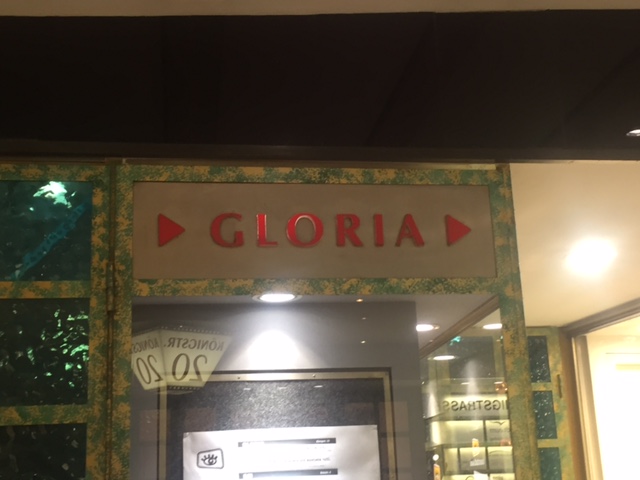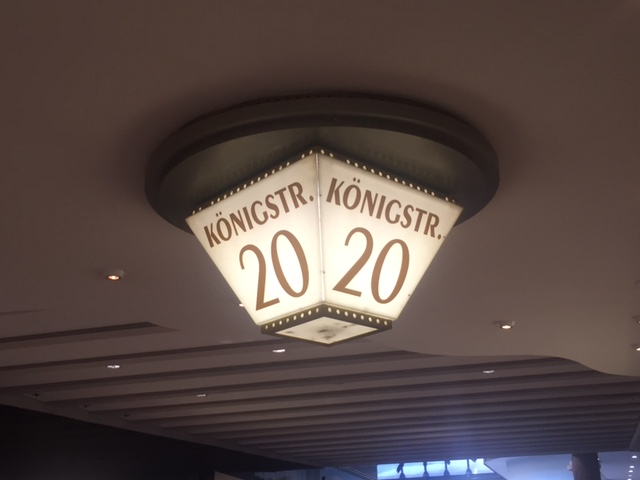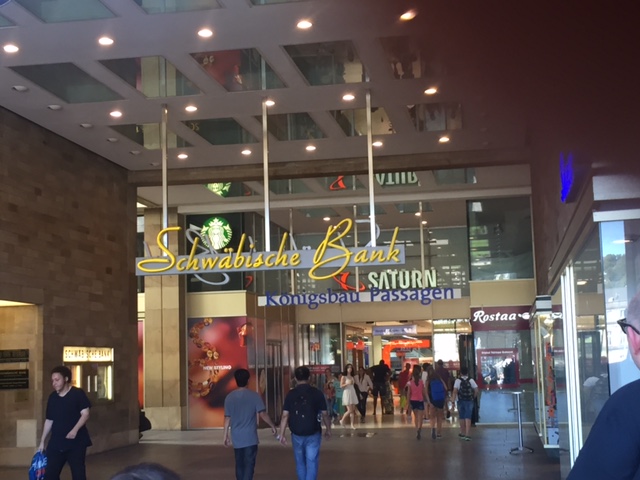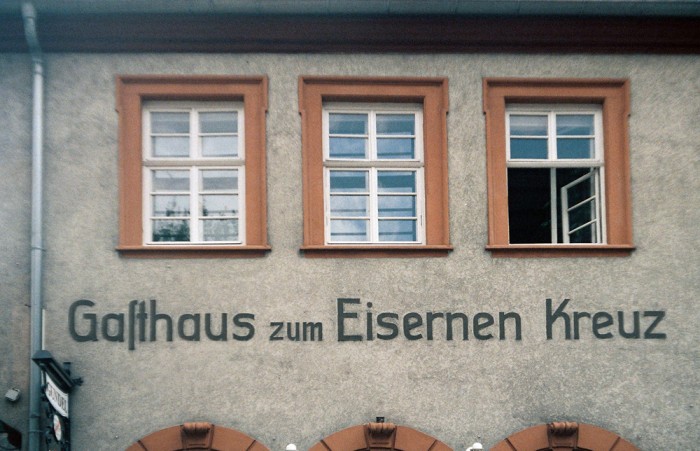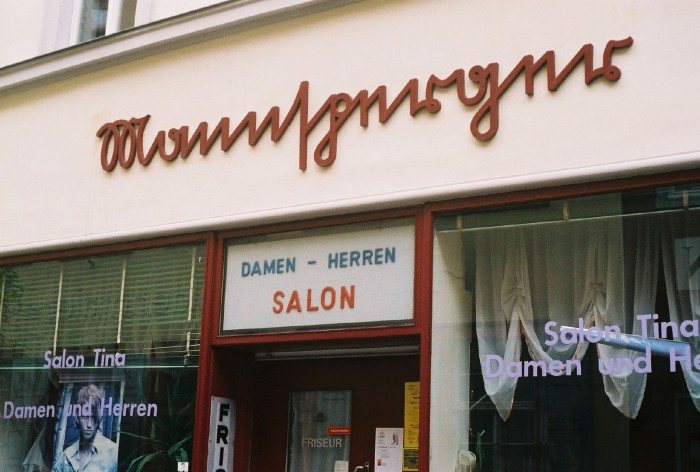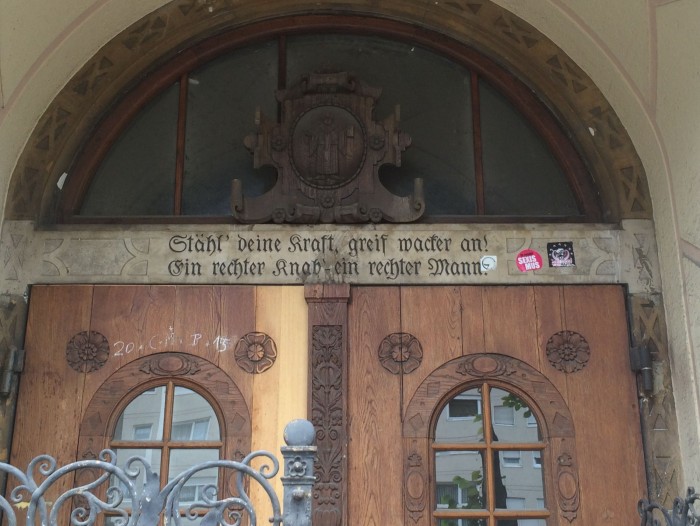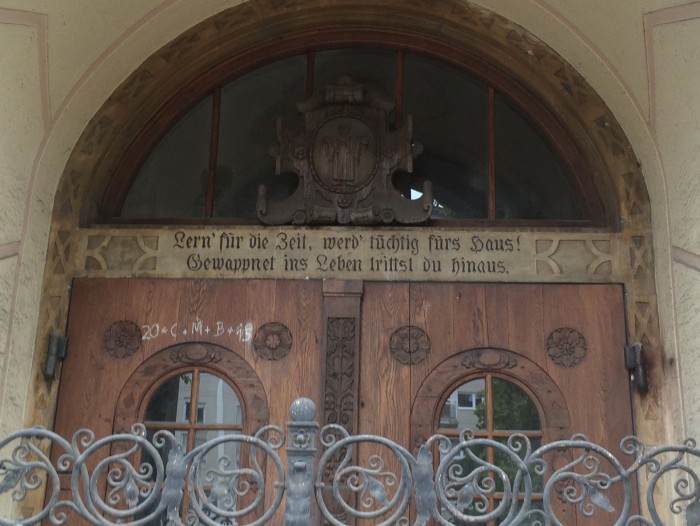
Typostreifzug durch die Stadt ...
Diesen netten Verstoß gegen die Lange-s-Regel habe ich in Heidelberg gesehen. Ist ja auch eine originelle Grotesk.
Und wahrscheinlich wollte der Schreiber ein wenig vom militärischen Ursprung ablenken, und hoffte, dass man an Eis denkt.
... was ihm auf jeden Fall gelungen ist – man sieht in diesen Tagen ziemlich viel Leute mit einem Eis in der Hand dort herumlaufen ;-)
Nochmal Heidelberg: Die meisten von Tinas Kunden werden das wohl eher nicht entziffern können.
Ich nehme an, dass der Schriftzug zu einem alteingesessenen Geschäft gehört hat.
Bei meiner – zugegebenermaßen oberflächlichen – Recherche konnte ich nichts darüber finden.
Sieht wunderschön aus, aber das ſ ist da doch auch falsch, oder? Ich hätte ja gedacht, daß das Manns-perger heißt, nicht Mann-sperger.
aber das ſ ist da doch auch falsch, oder? Ich hätte ja gedacht, daß das Manns-perger heißt, nicht Mann-sperger.
Im Prinzip stimme ich dir zu. Aber solange wir wegen der Herkunft des Namens nicht ganz sicher sein können ...
Die Optik könnte allerdings auch eine Rolle gespielt haben. Vielleicht hätte sich das runde s nicht so gut in den Namenszug eingefügt.
Oder der Name ist eben tatsächlich Mann|sperger. Namen Sperger und mit -sperger, wobei das s eben kein Fugen-s ist kenne ich ein paar.
Das ist dann so Ähnlich wie bei Neckarſulm, das eben auch die falsche Aussprache als das Ulm des Neckars ersat durch Aufgabe des langen s bekommen hart. Heute wissen nwenige, dass die Stadt einfach nur nach den Flüssen benannt wurde, die dort zusammen fließen, eben Neckar + Sulm = NecksrSulm = Neckarſulm = Neckarsulm
Ein anderes Beispiel, auch das Asperger-Syndrom wird ja A|sperger ausgesprochen, und nicht As|perger
Grundschule an der Fürstenrieder Straße in München-Laim. 1937 war die eine Tür für die Mädchen, die andere Tür für die Buben bestimmt. Heute teilt sich das nach Grund- und Mittelschule.